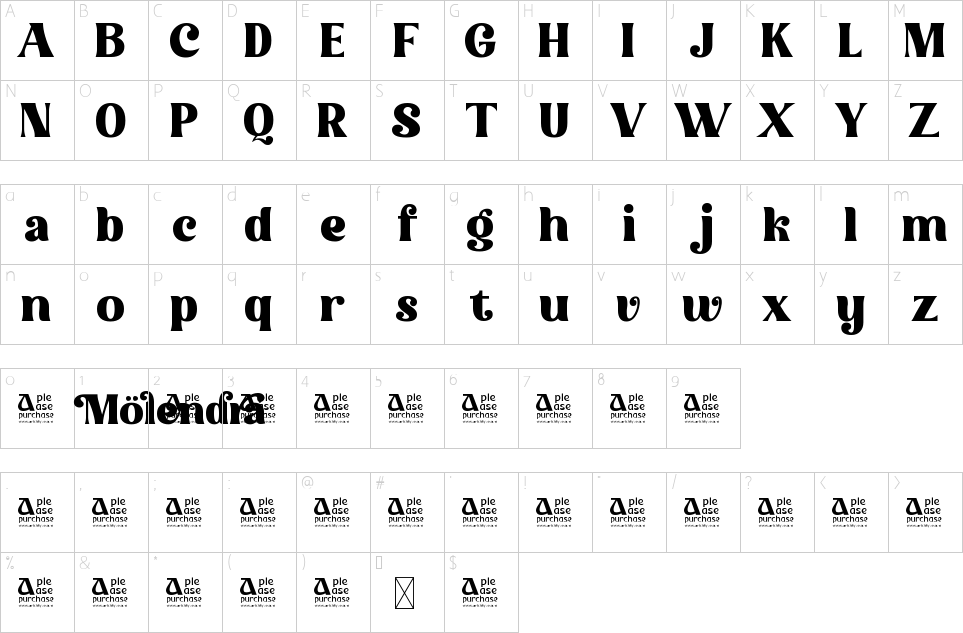
Descubra a elegância arredondada e fluida da Molendra Font para seus projetos digitais. Esta fonte foi criada pela Artchitype Studio, uma equipe dedicada que busca inspirar criatividade através de suas criações únicas. Com seu design minimalista e sua tipografia moderna, a Molendra é perfeita para uma variedade de usos – seja para criação de websites, logomarcas ou até mesmo como fonte padrão em documentos pessoais. Estendendo a conveniência de ter um recurso gratuito à disposição dos designers, o download da Molendra Font para os sistemas Windows e Mac está aqui. Com mais de 1.593 downloads confirmados, não há dúvida de que esta é uma opção popular entre muitos criadores. Se você está procurando por uma fonte fresca e moderna sem precisar gastar dinheiro extra, a Molendra Font pode ser a escolha perfeita para seu próximo projeto visual.